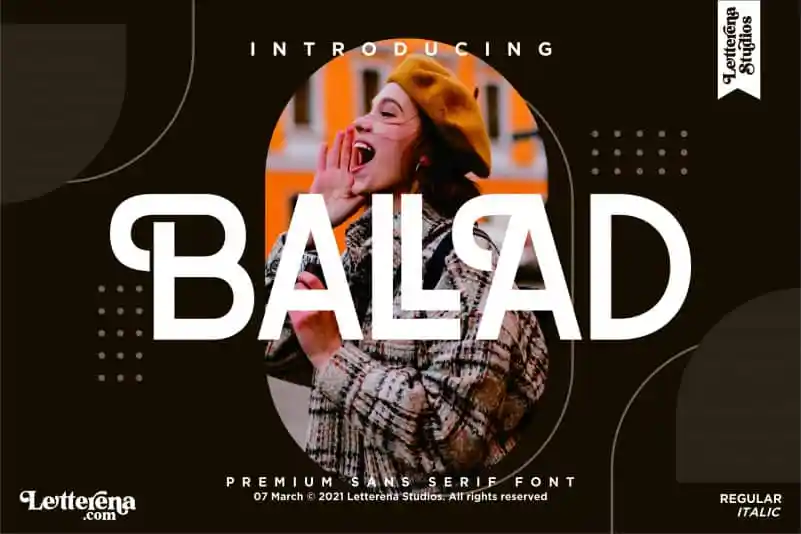
BALLAD Font – Fonte Grátis
BALLAD Font
A BALLAD Sans Serif é uma nova opção para designers apaixonados por linhas simples e modernas. Esta fonte é perfeitamente adaptada a uma variedade de projetos, desde criações de logomarcas e estilos de marca até designs de embalagens de produtos e materiais promocionais como etiquetas e cartões de visita. Seu design elegante se destaca em qualquer projeto que busque uma sensação sofisticada e luxuosa. Ideal para criar elementos únicos e atraentes, seja para capas de livros ou até mesmo mensagens de desejo personalizadas para eventos especiais. Esta fonte é perfeita para os designers que procuram um toque único e sofisticado em seus projetos.